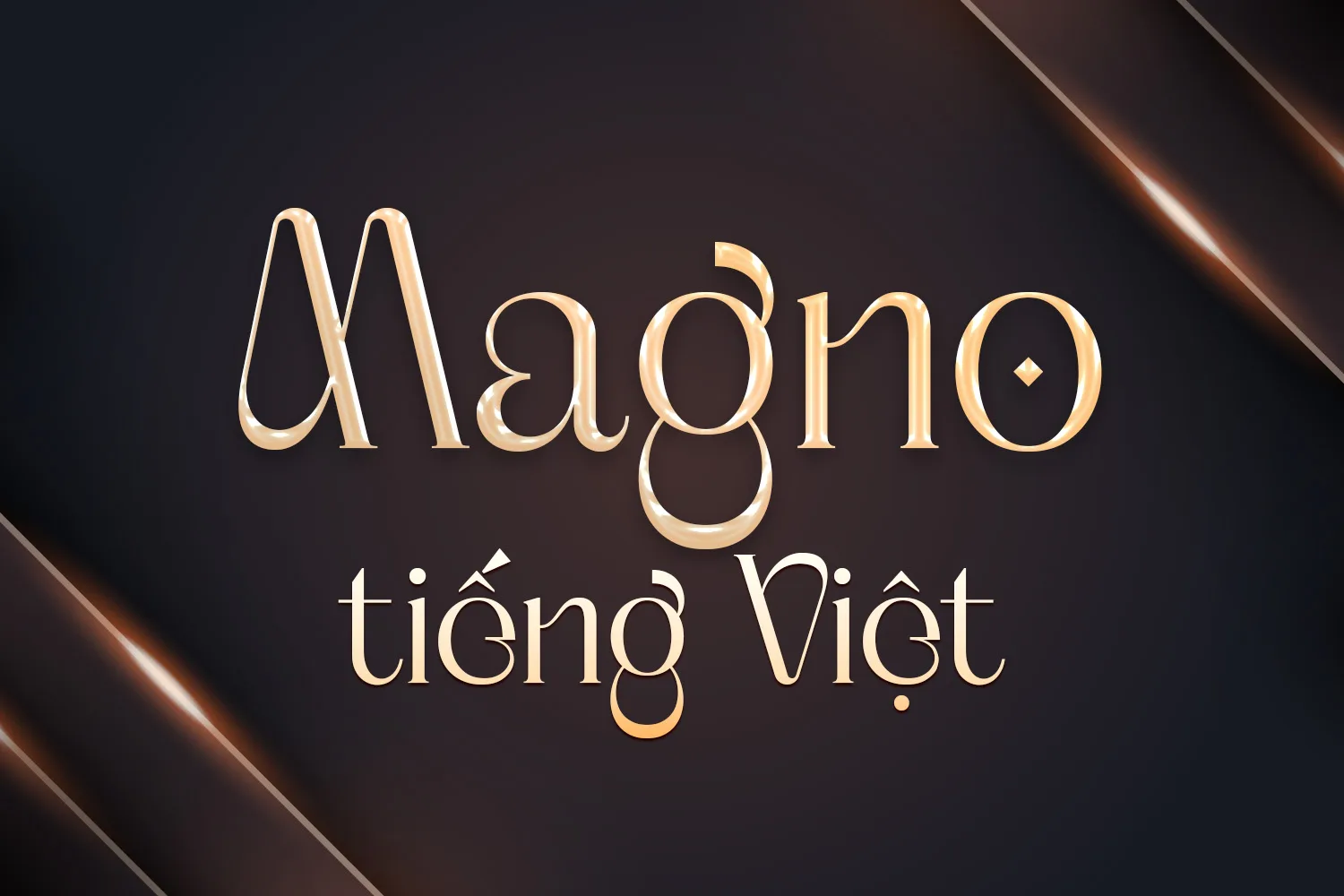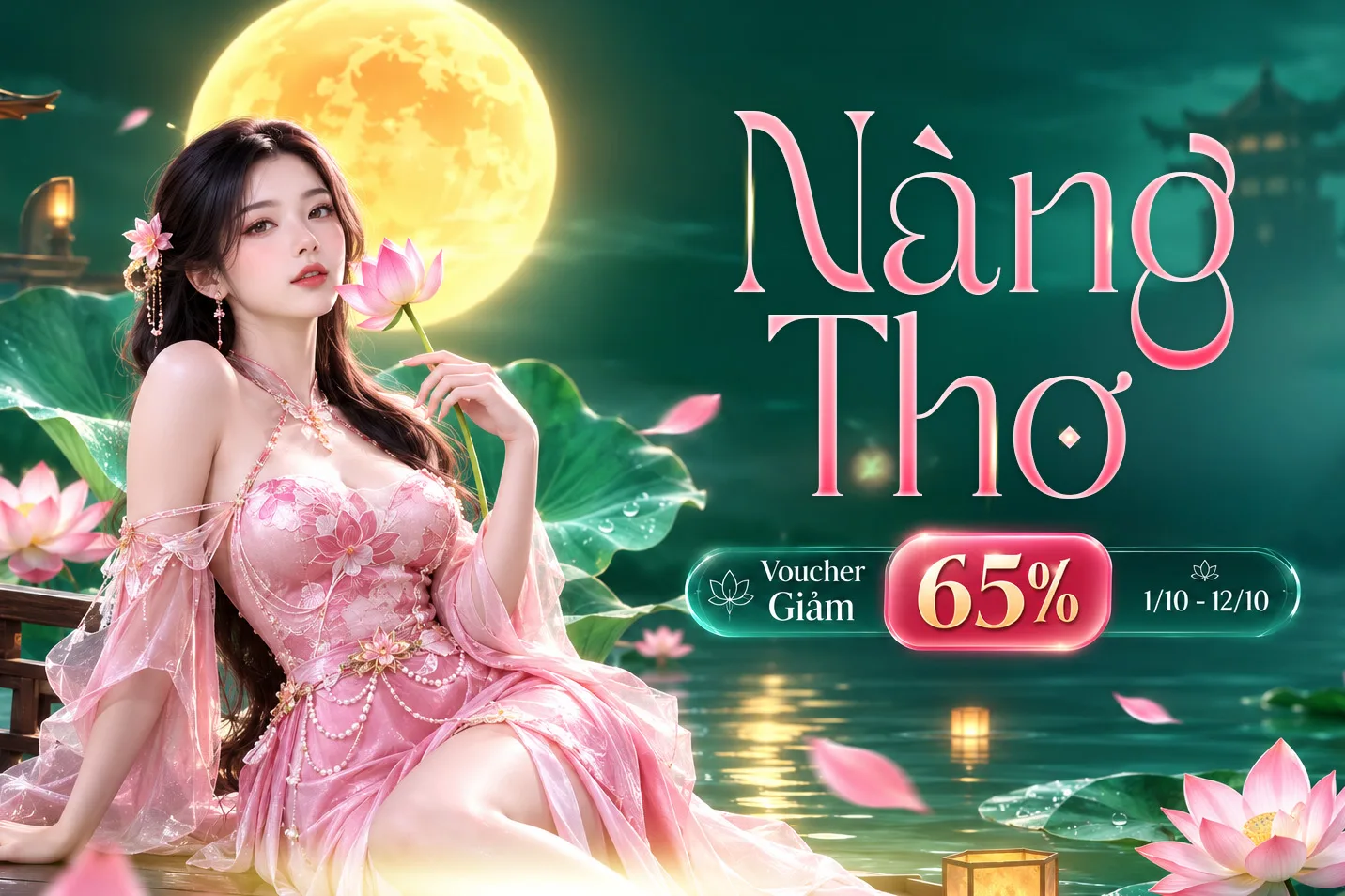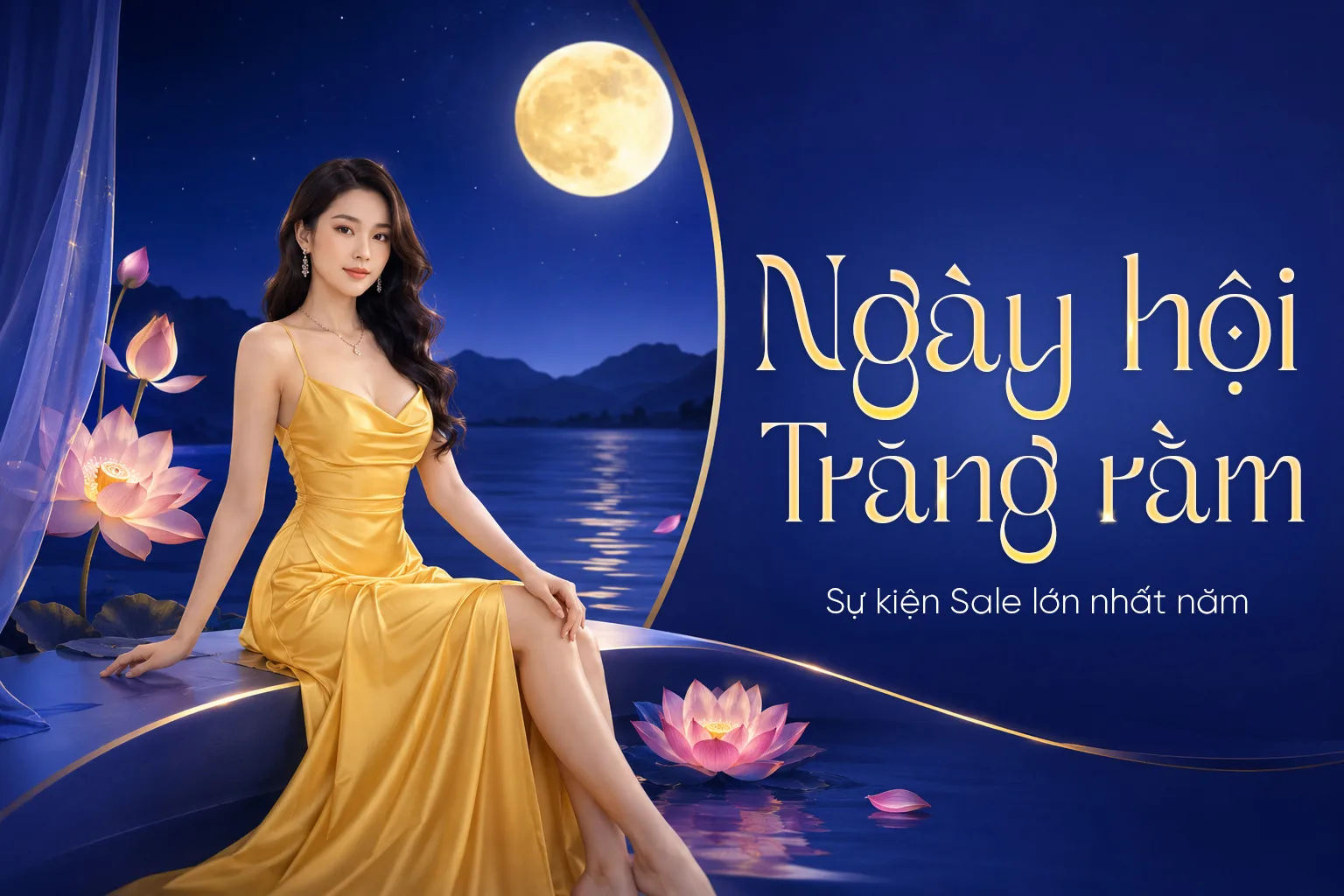
DVN Magno tiếng Việt – Font chữ Serif sang trọng và thanh lịch
DVN Magno là kiểu chữ serif cao cấp mang phong cách hiện đại, được thiết kế để tạo nên sự sang trọng, tinh tế và khác biệt trong từng ký tự. Với các đường nét thanh mảnh, tỷ lệ cân đối cùng hệ thống Alternate và Ligature được chăm chút kỹ lưỡng, DVN Magno giúp logo, tiêu đề và nhận diện thương hiệu trở nên nổi bật mà vẫn giữ được vẻ thanh lịch.
Font hỗ trợ đầy đủ tiếng Việt Unicode, bao gồm đầy đủ dấu, ký tự đặc biệt và Multilingual Support, phù hợp cho cả các dự án trong nước lẫn quốc tế. Đây là lựa chọn lý tưởng cho những thương hiệu theo đuổi phong cách luxury, fashion, beauty, jewelry, editorial, wedding, boutique hoặc các thiết kế mang tính nghệ thuật và cao cấp.